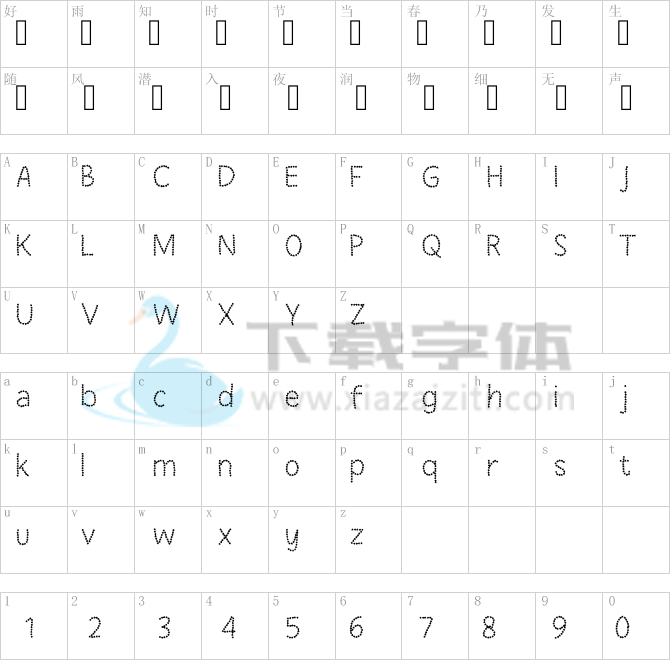
Alnair Star.ttf字体下载,这款字体结构工整、笔画清晰,兼顾美观与易读性,适用于标题、正文、海报、包装、LOGO 等多种场景。字形优雅稳定,风格百搭耐看,适配日常排版与创意设计,让文字呈现更舒适、更具质感。Alnair Star.ttf字体下载一笔一画,皆是细节,以均衡的比例、流畅的线条打造舒适视觉体验,字形端正大气,风格简约现代。无论是商业设计、品牌宣传还是日常排版,都能轻松驾驭,让文字更有格调与力量。Alnair Star.ttf字体下载字体下载。